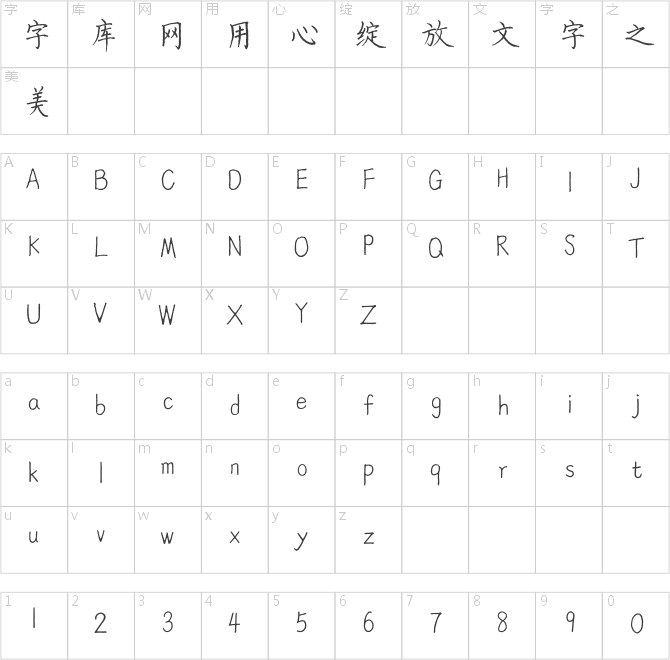
方正字迹-屈太侠清秀楷
方正字迹-屈太侠清秀楷,主要具有两大特点:长方字体,笔画光滑。这样的字体,特别适合作为模板,做成字帖,或者供中小学生、书法爱好者学习。当然,字体本身最大的特点就是“清秀”,作为广告设计字体使用,效果也不错。 作者屈太侠,专注于写字教学10年,科研成果《小学生写字教学有效性的研究》获广州市一等奖,出版写字类教学专著《走向有效的写字教学》。